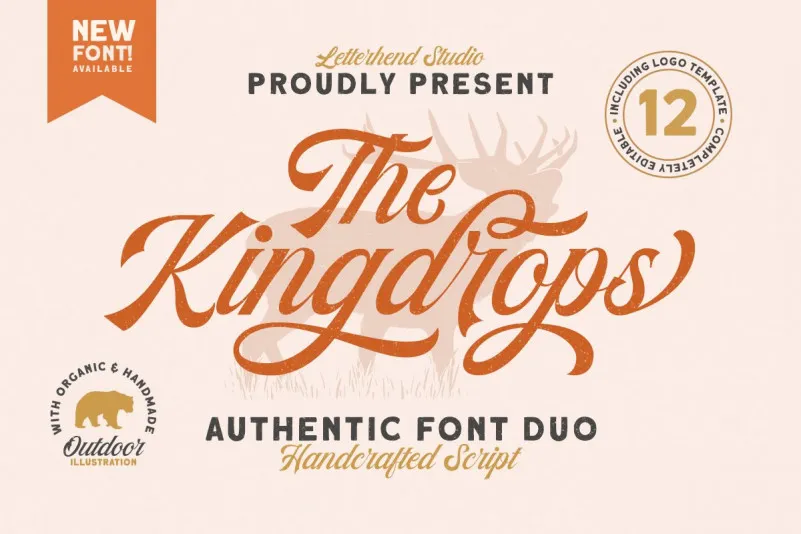
Kingdrops Calligraphy Font – Download Grátis
Descubra a beleza única do Kingdrops Calligraphy Font, uma deliciosa mistura de calligrafia moderna e versátil para qualquer projeto. Tradicionalmente inspirada na arte manual, esta chamada esculpida é perfeitamente adaptável à criação de logotipos, cartões de convite, rótulos, revistas, livros ou até mesmo embalagens de moda. O designer m@graphics criou uma fonte moderna e única que se sobressai na sua categoria. A proposta inclui 50 objetos desenhados à mão para uso individual, juntamente com 12 modelos pré-fabricados para logotipos. O resultado final é um conjunto de elementos gráficos incrivelmente bem executado, onde cada detalhe reflete a arte da escrita. Este é o duplo perfeito para quem procura uma fonte versátil e única para aplicação em qualquer tipo de projeto. Tudo pronto para rockar, desde cartas de cumprimento ou casamento até embalagens de moda e livros. Esta é uma excelente escolha para aqueles que desejam dar um toque especial a suas criações com a Kingdrops Calligraphy Font.
Designer: m@graphics